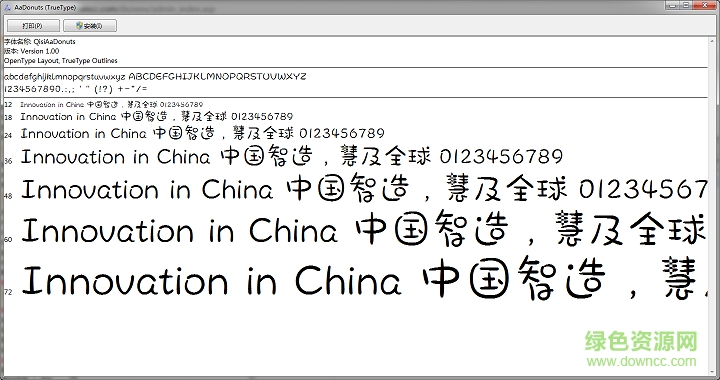
軟件介紹 軟件標(biāo)簽: aa字體 字體 aa甜甜圈字體ttf又名字體管家甜甜圈體,是一款非??蓯鄣闹形暮嗴w字體,輸入的每個漢字都像甜甜圈樣,很有特色,妹子們的最愛。趕快下載體驗吧!aa甜甜圈字體安裝方法一:控制面板/字體/文件/安裝新字體;方法二:直接將字體復(fù)制到C:\WINDOWS\Fonts。方法三:針對win7系統(tǒng),用戶只需選中字體右鍵安裝即可。使用說明本站所有字體資源僅供個人學(xué)習(xí)與參考,如需商業(yè)使用請到相關(guān)官網(wǎng)授權(quán)。 軟件截圖 上一張下一張(1 / 1) 安裝詳細截圖 猜你喜歡 aa字體 文悅字體 aa字體 aa字體大全包含了aa字體庫旗下所有字體安裝文件!aa字體系列非常受廣大網(wǎng)友的喜愛,涵蓋了各種個性化的字體,可以設(shè)計廣告、商業(yè)logo等!有需要的用戶歡迎來綠色資源網(wǎng)下載。 查看更多>> aa小軟糖字體 4.37M/中文/10.0/下載 Aa名字被貓叼走了字體 3.75M/中文/10.0/下載 aa云深不知處字體ttf 4.15M/中文/2.0/下載 aa薄荷少年字體 37.01M/中文/10.0/下載 aa初戀微甜拼音字體 4.80M/中文/10.0/下載 Aa云想衣裳花想容體 4.57M/中文/10.0/下載 文悅字體 文悅字體是由文悅科技推出的字體,雖然總體數(shù)量不多,但是,每款字體都很有特點,如:文悅古體仿宋、文悅古典明朝體等,對于一些喜歡特色字體的朋友來說,文悅字體是不錯的選擇。 查看更多>> 管家方萌字體 1000KB/中文/5.0/下載 aa甜甜圈ttf字體 2.65M/中文/10.0/下載 文悅聚珍仿宋 4.74M/中文/10.0/下載 文悅古典明朝體 3.22M/中文/3.6/ttf版下載 文悅古體仿宋 13.67M/中文/6.6/ttf版下載 文悅青龍體 5.85M/中文/8.1/下載 其他版本下載 標(biāo)題 大小 更新日期 下載 aa紙膠帶字體 1.55M 2017-10-24 下載 aa小鹿體字體 7.06M 2017-02-15 下載 Aa小點點字體 ttf 7KB 2017-02-28 下載 aa言葉之庭字體mtz 124KB 2017-03-08 下載 Aa印象手帳體ttf 4.79M 2017-07-23 下載 aa夕禾字體 ttf版 5.50M 2017-05-18 下載 aa方萌字體 2.44M 2017-12-14 下載 Aa十七歲的夏天字體 ttf免費版 3.65M 2019-02-25 下載 Aa橘子味的熊字體 3.53M 2019-02-25 下載 Aa偷偷喜歡你拼音體 ttf免費版 4.58M 2019-02-25 下載 下載地址 電腦版 aa甜甜圈ttf字體 點擊報錯 軟件無法下載或下載后無法使用,請點擊報錯,謝謝! 關(guān)閉報錯反饋 請描述您所遇到的錯誤,我們將盡快予以修正,謝謝! *必填項,請輸入內(nèi)容 本類最新 dreamweaver字體庫 首爾南山體字體 v1.06 官方版 潮字社風(fēng)云簡ttf 潮字社凌渡鯤鵬簡體字體 潮字社曾玉波手書簡字體 微博慧心字體 相關(guān)文章 Photoshop字體安裝使用方法和技巧 如何解決“無法新增字體”問題 Win 7系統(tǒng)安裝字體方法 網(wǎng)頁字體大小設(shè)置方法 怎么改網(wǎng)頁字體大小 在Linux系統(tǒng)中安裝字體的幾種方法 windows7字體顯示問題:打開某些程序的時候顯示的是亂碼 用戶評論 熱門評論 最新評論 發(fā)表評論 查看所有評論(0) 昵稱: 請不要評論無意義或臟話,我們所有評論會有人工審核. 字數(shù): 0/500 (您的評論需要經(jīng)過審核才能顯示)